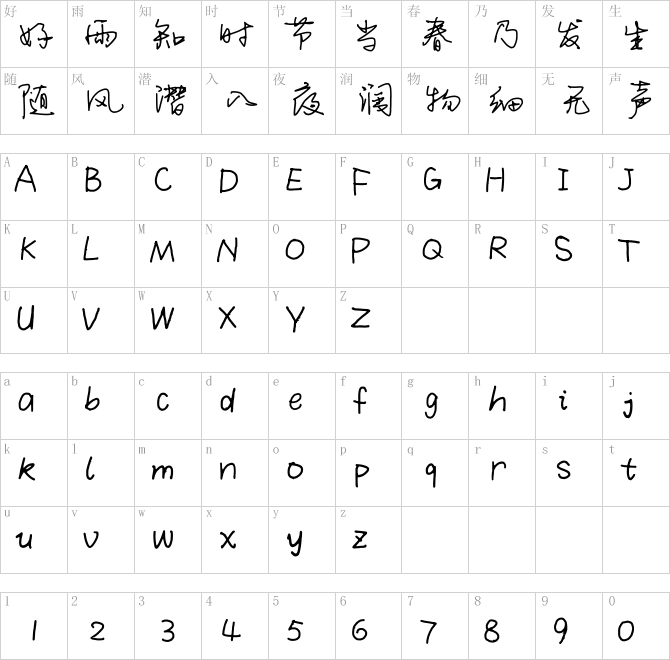
黑梦追夜体.ttf,这款字体结构工整、笔画清晰,兼顾美观与易读性,适用于标题、正文、海报、包装、LOGO 等多种场景。字形优雅稳定,风格百搭耐看,适配日常排版与创意设计,让文字呈现更舒适、更具质感。黑梦追夜体.ttf一笔一画,皆是细节,以均衡的比例、流畅的线条打造舒适视觉体验,字形端正大气,风格简约现代。无论是商业设计、品牌宣传还是日常排版,都能轻松驾驭,让文字更有格调与力量。黑梦追夜体.ttf字体下载。
黑梦追夜体.ttf是一款默陌字库出品的书法字体,目前已经发布了50款+字体